明年的古偶101,我不做选择,我都要看~
每年的古偶剧,都是各大平台的香饽饽,因为太容易爆了,你看今年就爆了《星汉灿烂》和《苍兰诀》,可你知道明年有多内卷吗?就准备排播的,刚刚杀青的,以及正在拍摄的就有十几部……
这对观众来说当然是福音,你们越卷,我们就越不会剧荒,大不了买个爱优腾超级会员,用时间管理大法追剧。可对古偶剧来说,赛道更拥挤了,在班底都很厉害的情况下,只能是拼剧情,拼演技,拼美感了~
说到美感,虽然剧还没出来,但是海报啊,剧照啊,预告啊,都陆续能看到,谁能第一时间从视觉上脱颖而出,相信大家都有自己的pick,不过柚子正好利用会员新字,攒了一个自己心中的古偶排行榜,你怎么看?
点字烈金体 x 与凤行
刚刚杀青的与凤行自然是最期待的,楚乔和宇文玥的二搭,多少cp粉又复活了,加上又是九鹭非香的作品,剧情有保证,我只想说,后期gkd!
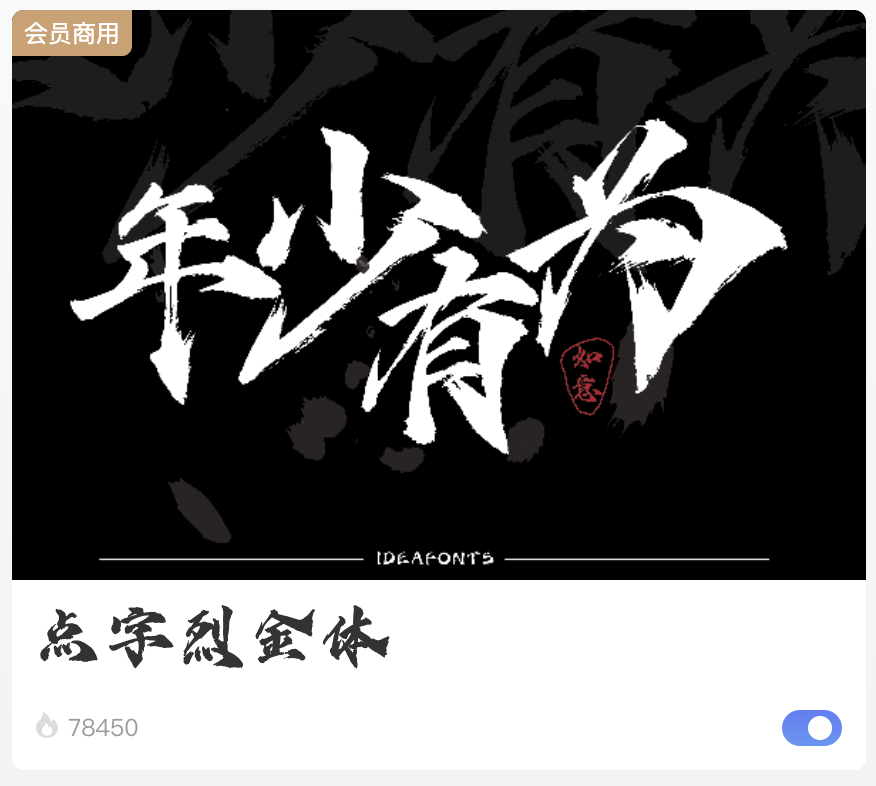
默陌狂飞侠客体 x 狐妖小红娘
狐妖小红娘也是前几天放出了杀青特辑,不得不说,这部剧妆造太好看了,还用了很多非遗的技艺,女演员又都是神仙打架,只要剧情不魔改,期待值直接拉满!
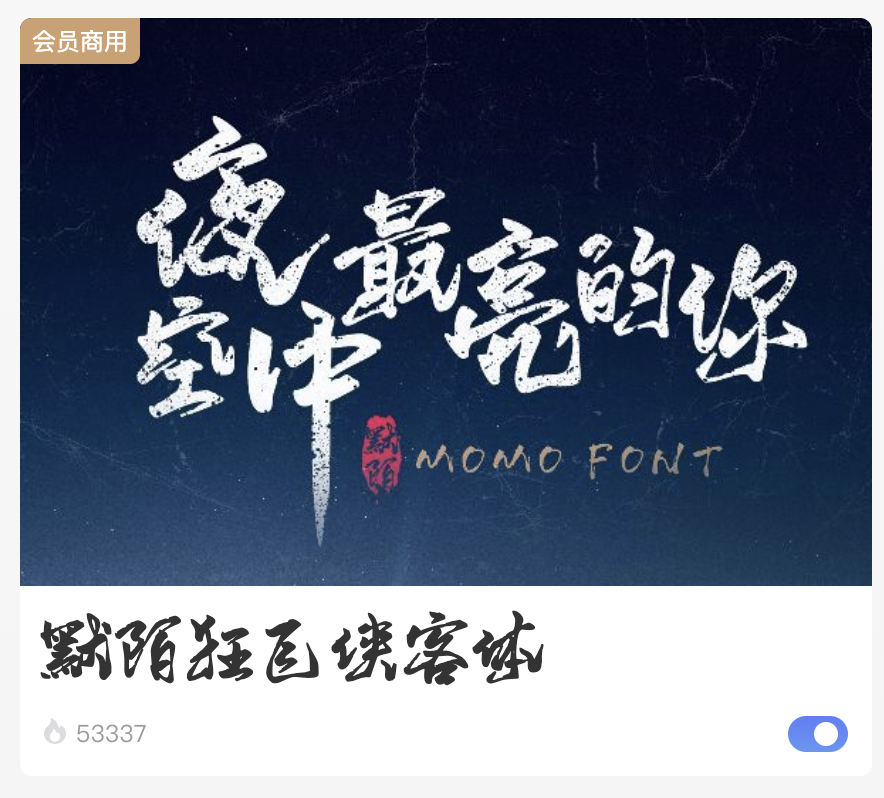
演示少年行 x 长月烬明
这部剧早就杀青了,拍在宁安如梦之前,也是非常想看的,毕竟你永远可以相信罗云熙的古装,而且这部剧的妆造也是非常能打,采用了敦煌美学,故事也非常曲折离奇,就问你,谁不想看突破次元壁的澹台烬!
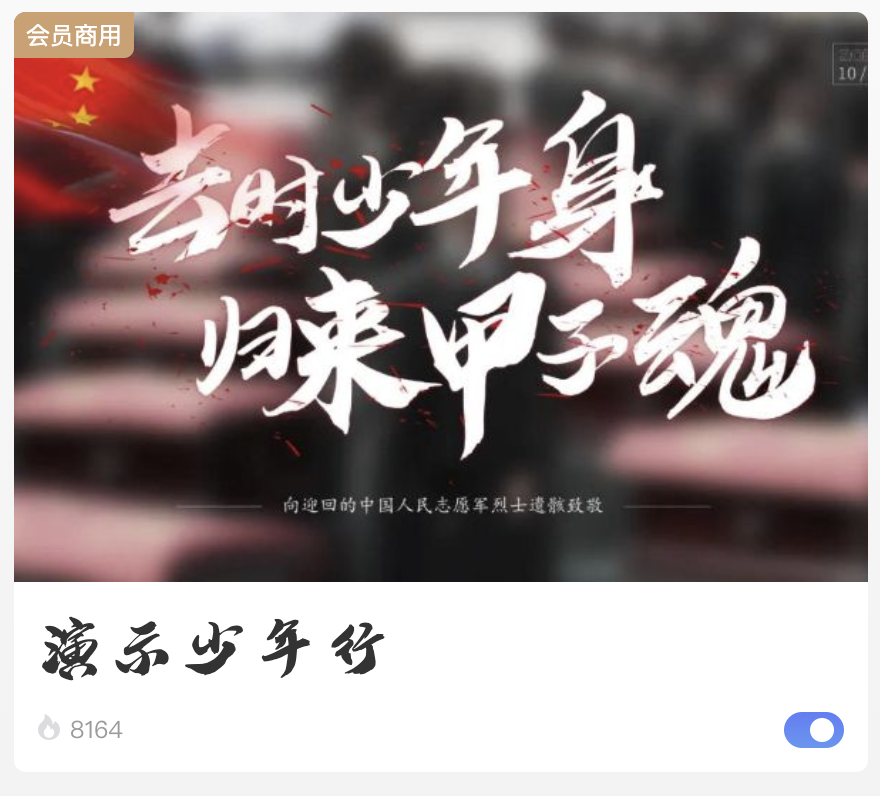
点字俊隶 x 长相思
长相思也是很多人期待的剧,毕竟有四个男性角色,光看片花,就够虐的,再加上杨紫的演技从来没让人失望,那就浅浅相思一下吧。
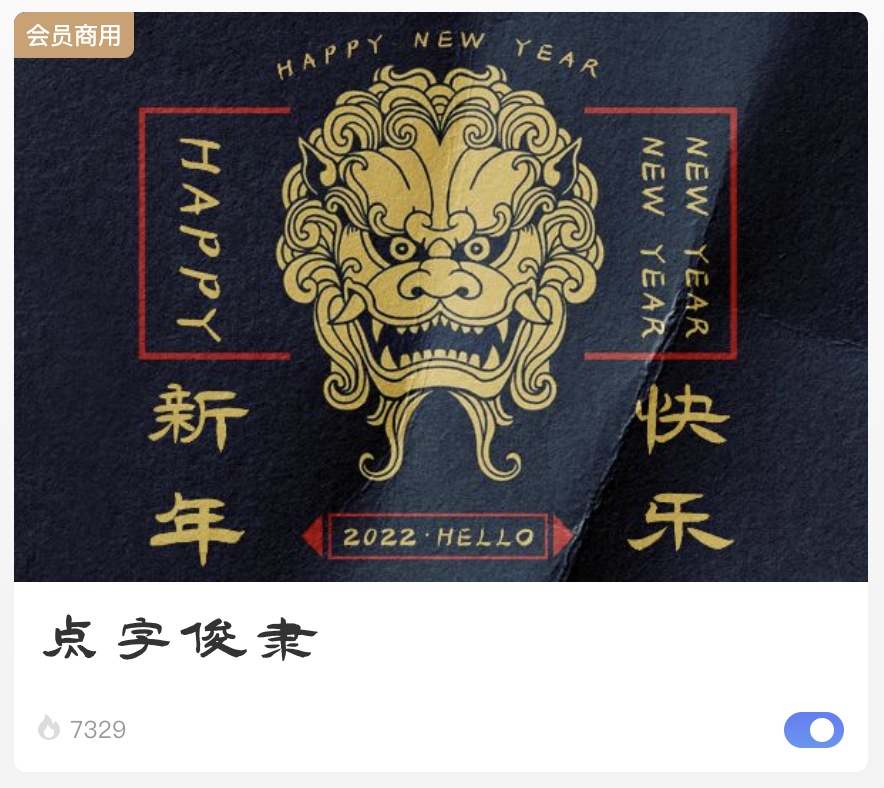
演示新手书 x 安乐传
安乐传应该是被压了的一部剧,迟迟不定档,只能排到明年,观看热情自然会被消耗,不过这也是热巴近期仅存的一部古偶了,喜欢她和龚俊的不要错过。
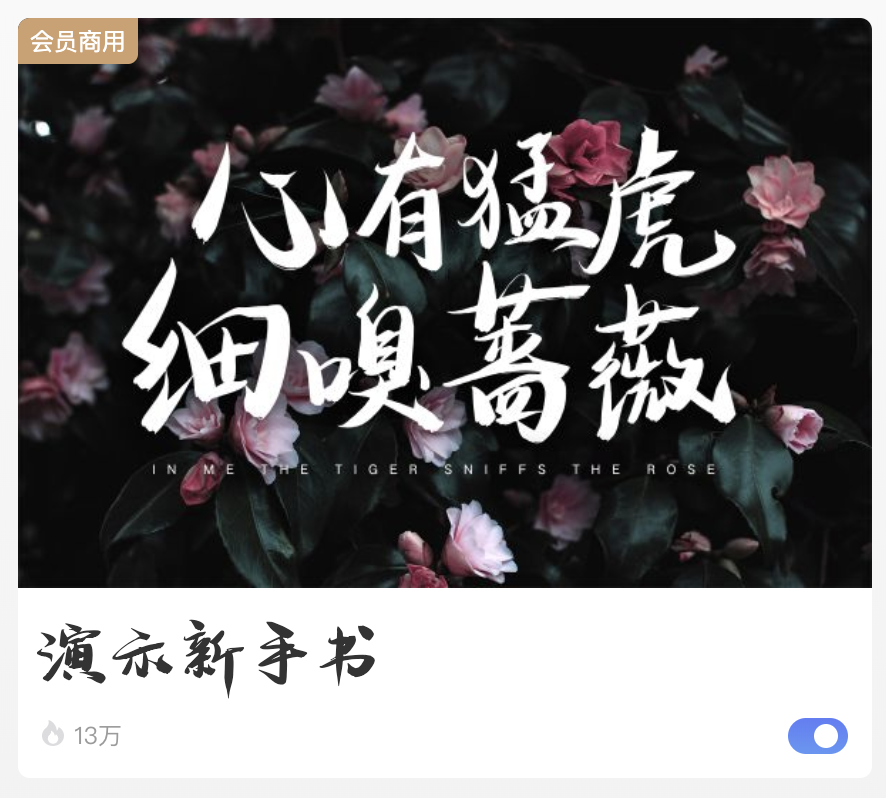
点字秀峰体 x 七时吉祥
喜欢苍兰诀的,应该也会喜欢七时吉祥,同一个作者,同一个恒星引力 ,据说长珩仙君还在里面客串了一下,高配置有了,就看年轻人的CP感和演技了。
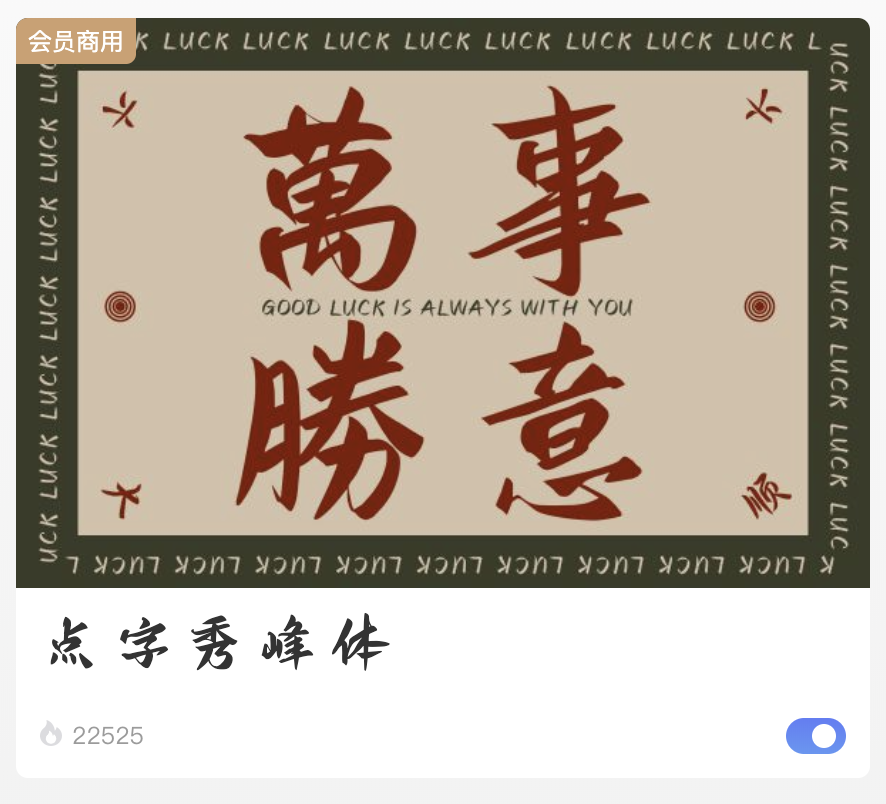
点字云辰 x 宁安如梦
虽然比长月烬明后拍,但没准会先播,毕竟要趁着演员的热度,感觉是权谋类型。
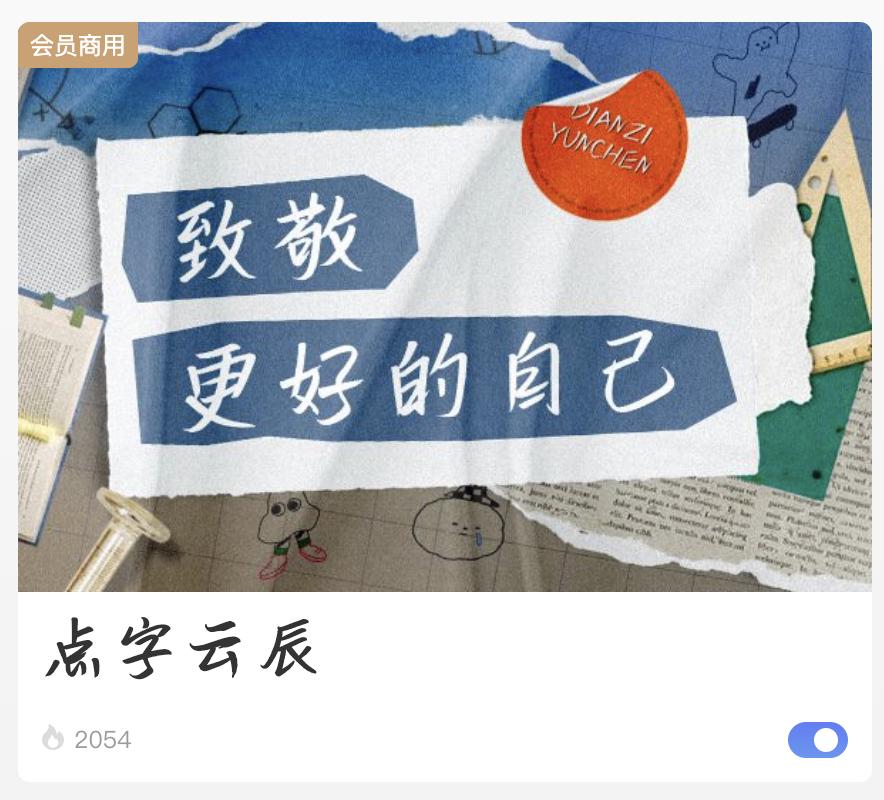
点字蒲尧凌云体 x 长风渡
好久没有看到小白的古装剧了,也是11月7日才杀青,期待顾九思早日上班。
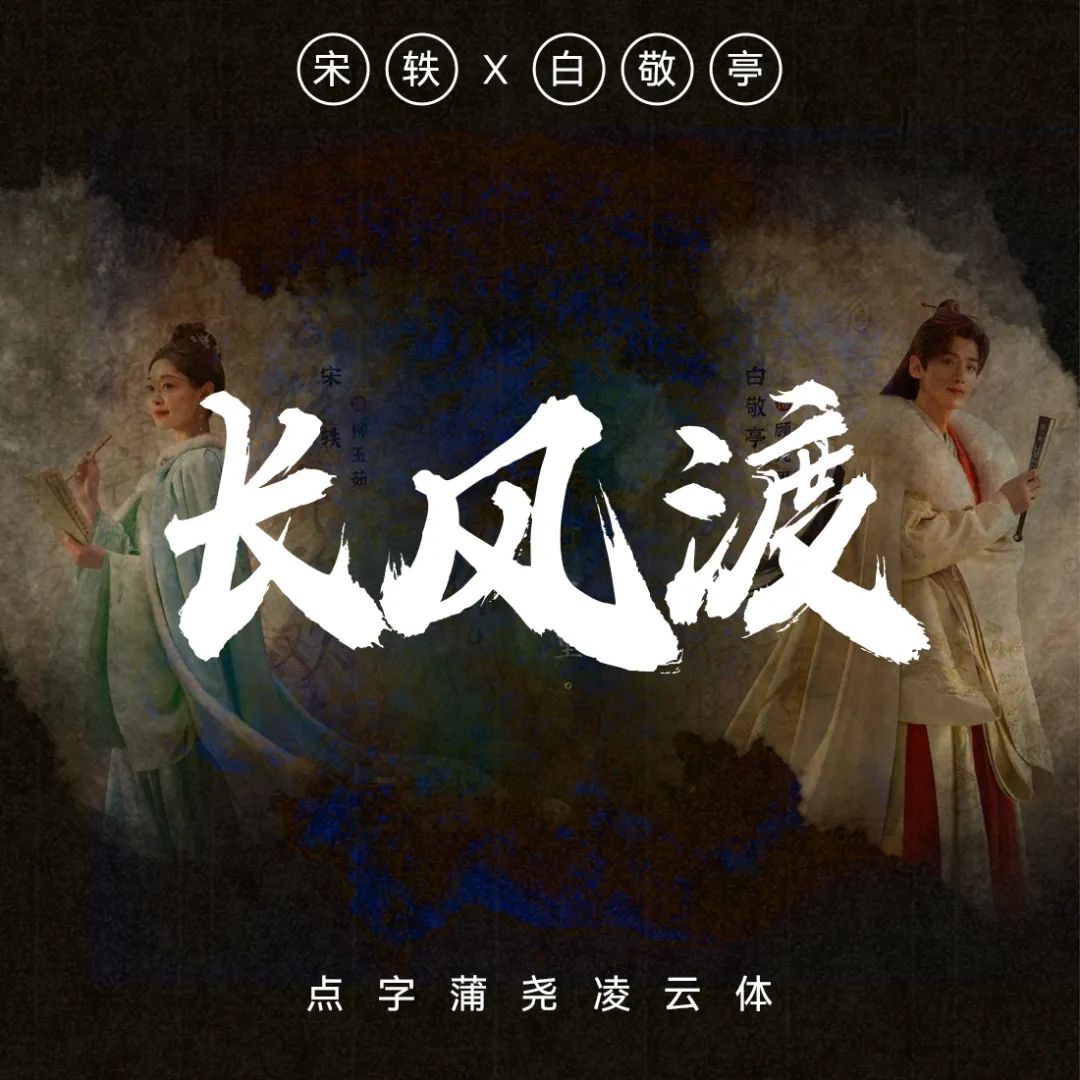
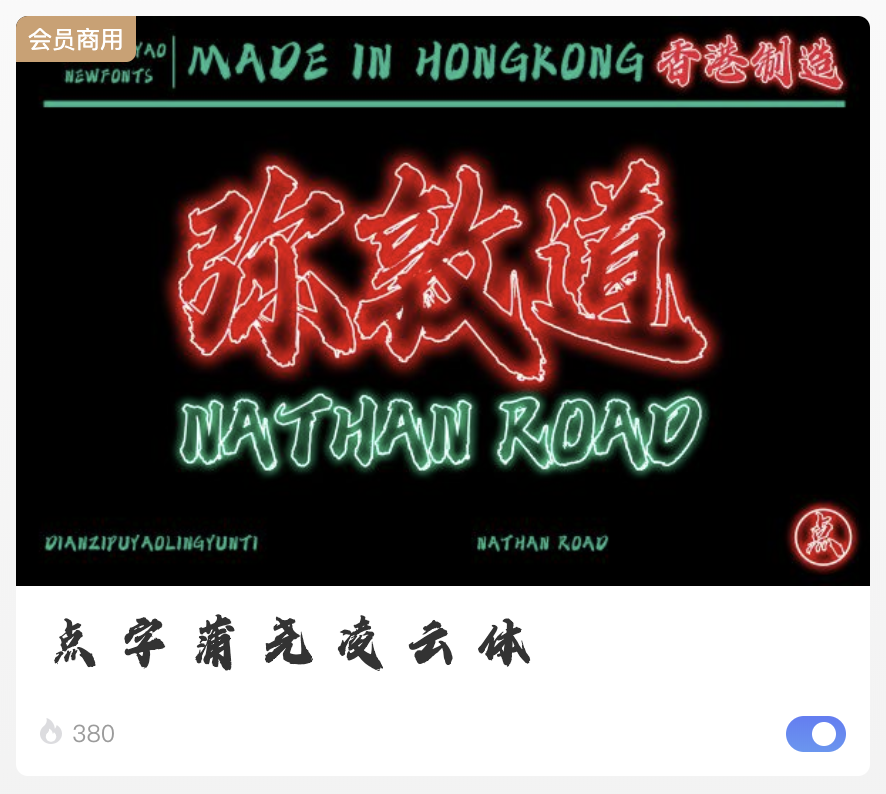
点字浩魂 x 一念关山
这部剧应该还在拍摄中,看海报感觉是武侠剧,不过冲着刘诗诗,也可以关注一下。
点字阿庆燃体 x 云襄传
之前播梦华录的时候,网友就在说古装不能没有陈晓,但陈晓好像更喜欢现代剧,所以这部云襄传算存货了,珍惜吧。
罗列了十部剧,发现有六部都是爱奇艺的,这还没包括《无忧渡》、《莲花楼》等,奇异果明年真的赢麻了,会员份子钱记得提前准备好~